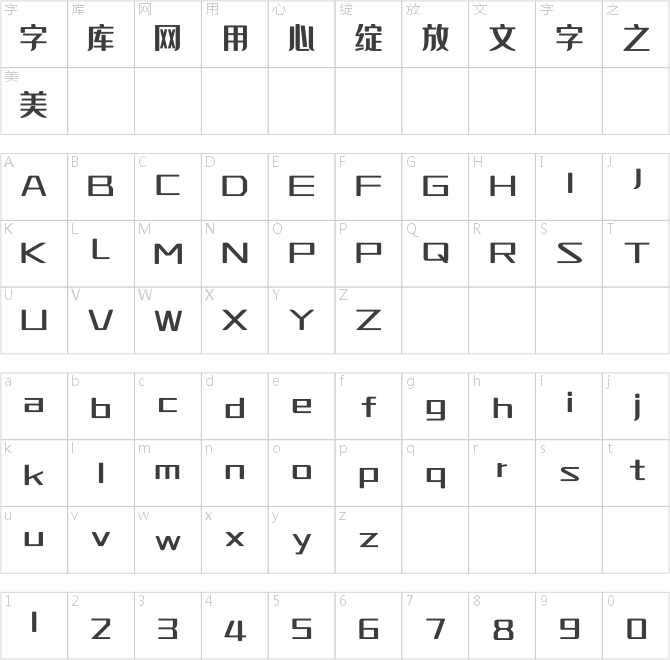
上首潤黑體,字體風(fēng)格方正柔麗,結(jié)構(gòu)豎筆橫筆都有導(dǎo)圓處理,豎勾做了簡化處理,有的字內(nèi)部進(jìn)行了斜對角導(dǎo)圓,為此套字的亮點。
上首潤黑體字體字庫是一款讓人賞心悅目、百看不厭的中文字體,適合各類廣告和產(chǎn)品包裝設(shè)計應(yīng)用,字體大小3.44MB,格式為ttf字體,上傳用戶是上首造字,作者/版權(quán)方為上首造字